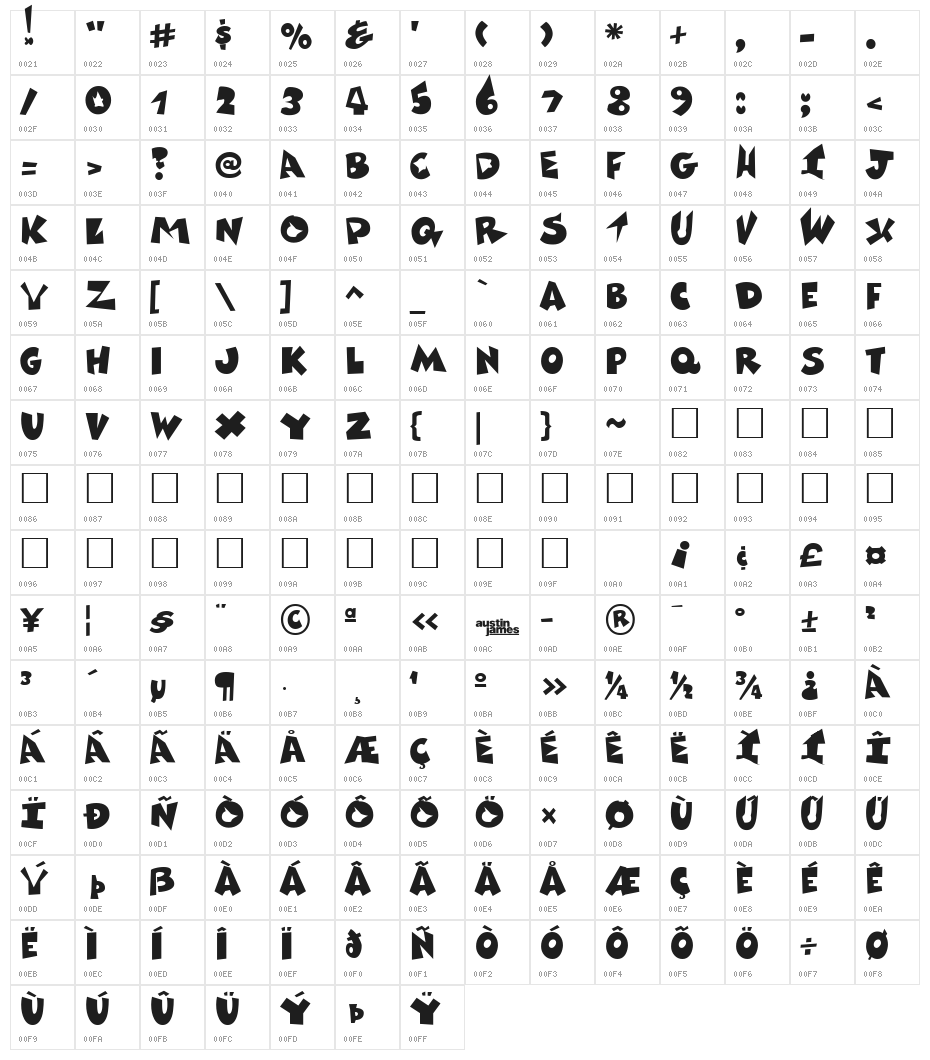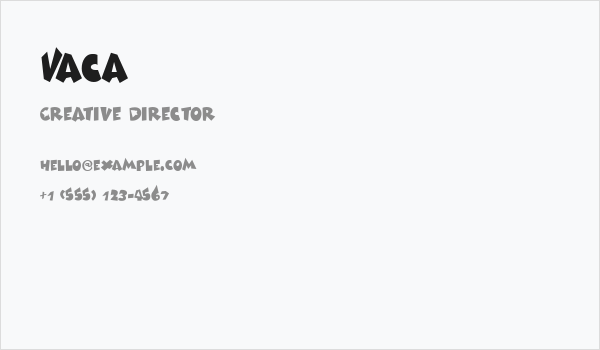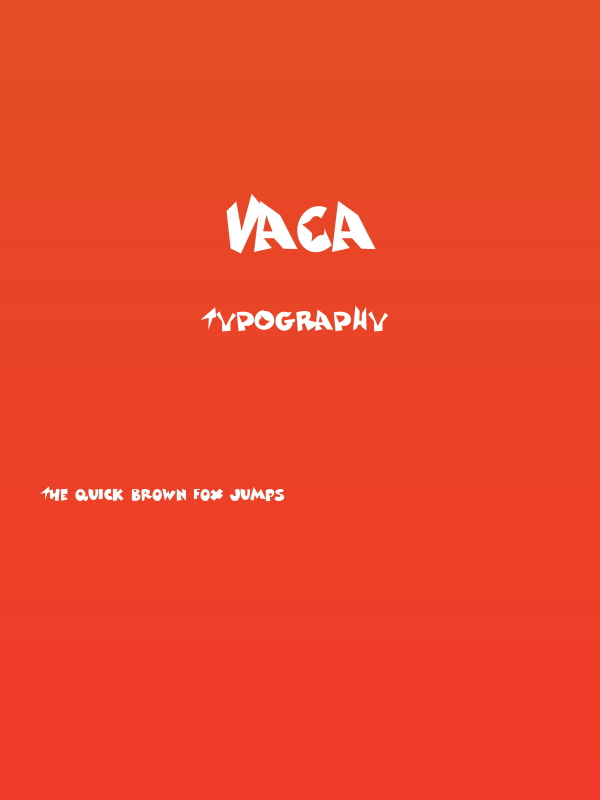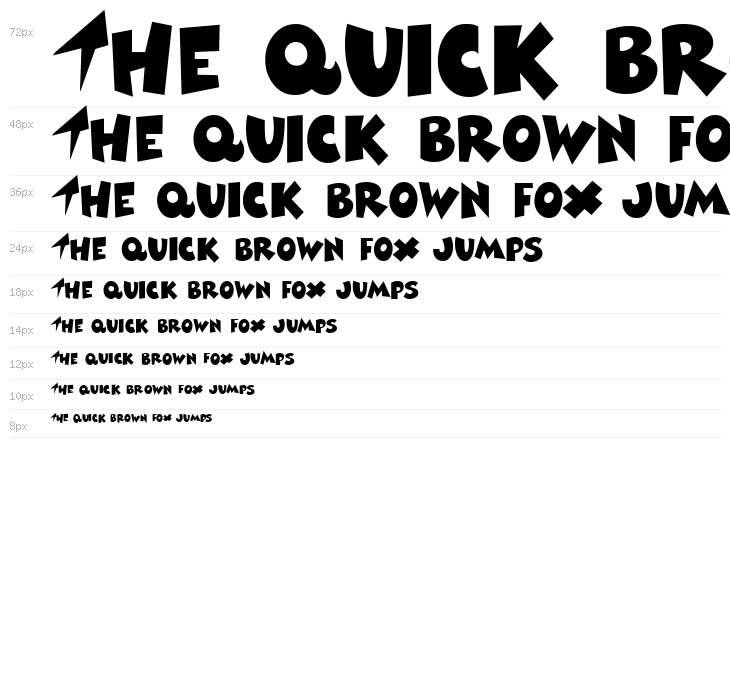
Vaca Font
| Stile generale | Playful, Energetic, Cartoonish |
| Progetti proposti | Ideal for children's books, comic strips, playful branding, and event posters. |